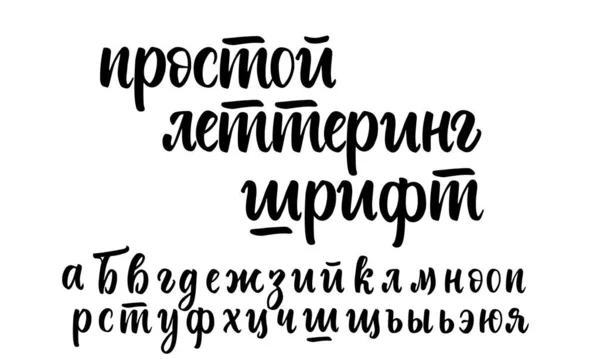
Курс рассчитан на пользователей Windows (но может подойти и для обладателей MAC ОS). Техника создания рукописных шрифтов подана очень подробно и направлена на достижение профессионального уровня работы. Вы узнаете технику создания шрифта от прорисовки букв на бумаге, до чистки и обработки Иллюстраторе и сборки в шрифтовой программе Glyphs. Также я покажу как создавать презентацию для шрифта и продавать его на таких сайтах как Креатив Маркет и ему подобные.
Основная часть работы — сборка шрифта будет проходить в программе Glyphs. Она очень удобна в работе и имеет ряд преимуществ, поэтому я работаю именно в ней.
Один из моих шрифтов
видео превью Hello January — Каллиграфический Шрифт Курсив с кириллицей
Каллиграфический свадебный шрифт с киррилицей Sadlyne — Подробный состав коллекции.
Кроме набора основных заглавных и двух наборов строчных букв, латиница шрифта включает 3 набора строчных букв с начальными и конечными завитками, а также 27 лигатур для двойных сочетаний букв, придающих реалистичный стиль. Кириллица также содержить формы строчных букв с начальными и конечными завитками и лигатуры. В дополнение к шрифту идет шрифт символов Sadlyne symbols — содержащий 36 нарисованных от руки элементов, иллюстраций и штрихов, которые станут органичным дополнением для вашего дизайна логотипов или свадебных приглашений.